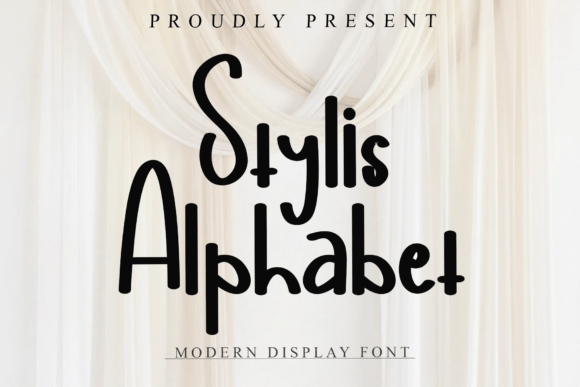
Stylis Alphabet
適切なデザイン要素を見つけるのは難しい場合がありますが、Stylis Alphabetは作品を即座に引き立てる優れたコレクションを提供します。
POD(オンデマンド印刷)製品、結婚式の招待状、またはソーシャルメディアのグラフィックを作成している場合でも、Stylis Alphabetは理想的です。